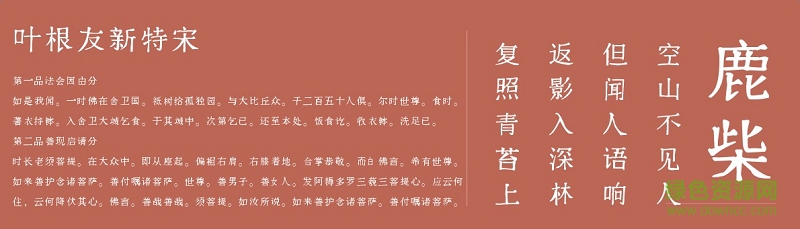
葉根友新特宋字體是一款全新的葉根友電腦字體,是在宋體的基礎(chǔ)上創(chuàng)造而來的,體樸茂工穩(wěn)、靈秀清麗、結(jié)體嚴(yán)整,非常適合用來制作各種設(shè)計(jì),喜歡就來綠色資源網(wǎng)下載!
葉根友新特宋是款在傳統(tǒng)宋體創(chuàng)意上延伸的藝術(shù)字體,字體的出現(xiàn)就注定了風(fēng)格的不同于尋常宋體。這款字體在傳統(tǒng)宋體的基礎(chǔ)上進(jìn)行了改進(jìn)創(chuàng)作,字型更加新穎有趣,非常適合各種海報(bào)廣告設(shè)計(jì)!